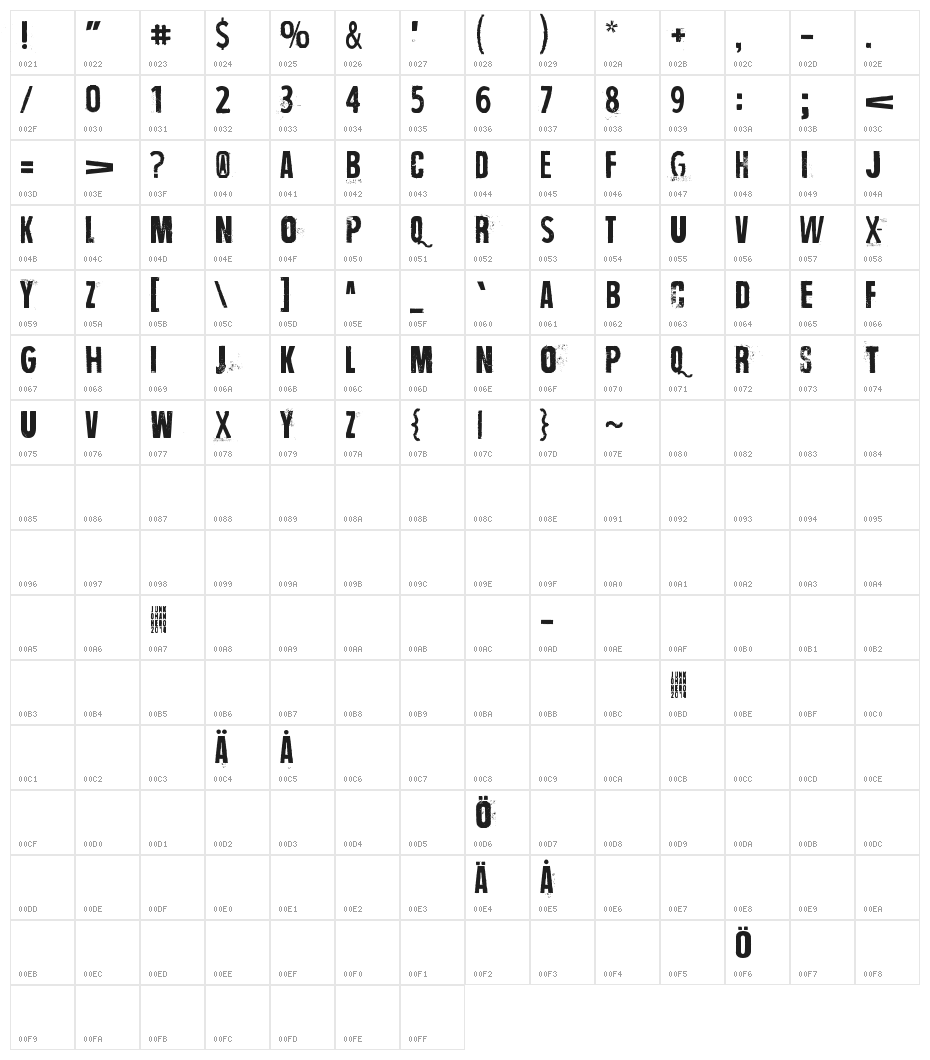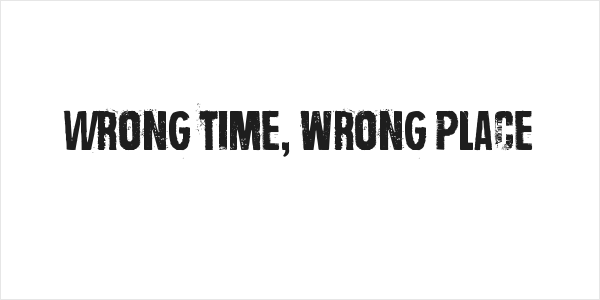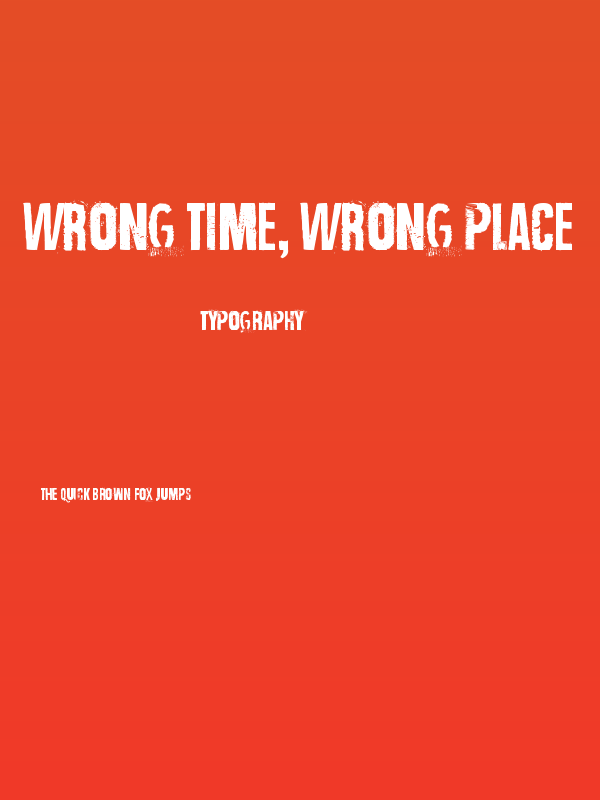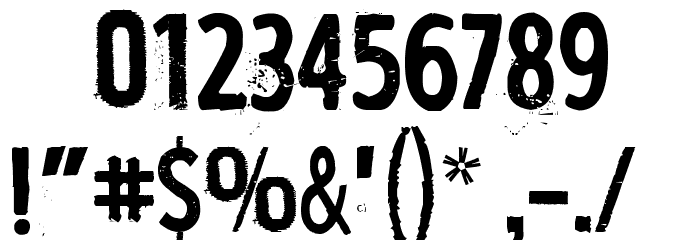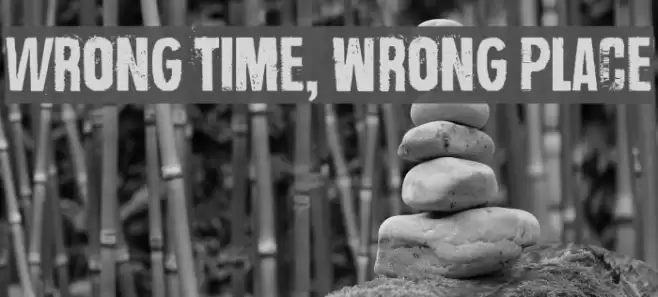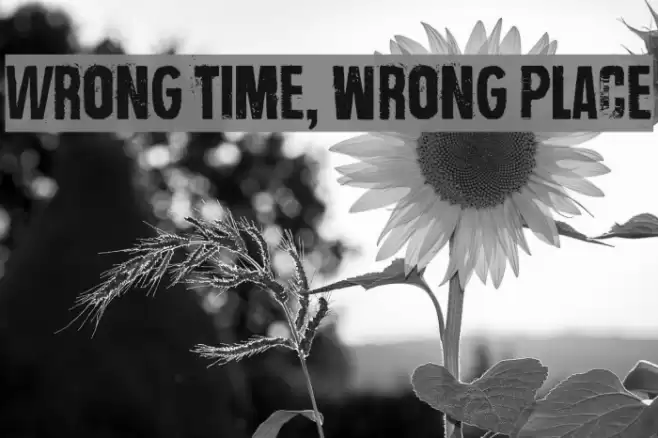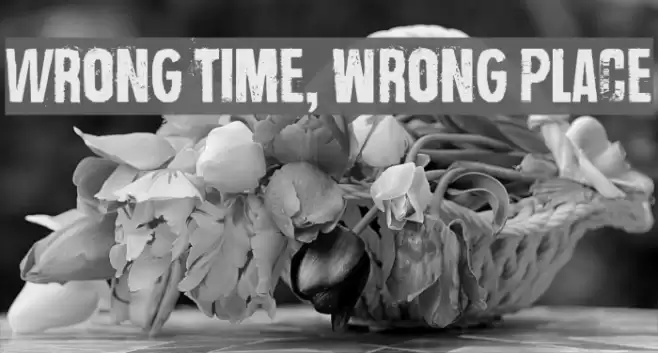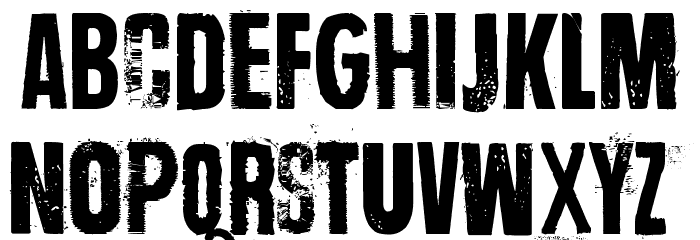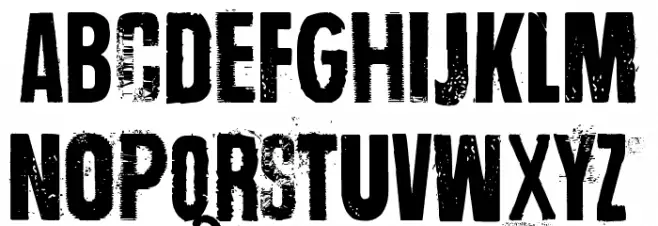
Wrong time, wrong place Font
| النمط العام | Vintage, Grunge |
| مشاريع مقترحة | Ideal for posters, album covers, branding for edgy or retro-themed products, and any design needing a bold, textured look. |